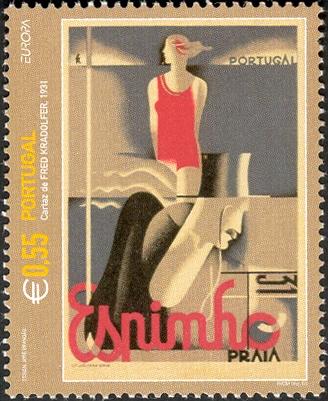
Fred Kradolfer (Zurique, 1903 - Lisboa, 1968)Chegado a Portugal em 1928, este suíço foi o mentor das artes da decoração e da publicidade para a segunda geração de artistas modernistas.Artista multifacetado, impulsionou o desenvolvimento das artes gráficas em Portugal, tendo usado a sua criatividade em diversos meios, do cartaz ao vitral, da cerâmica aos anúncios luminosos. Fred K. foi o gráfico que revolucionou o cartaz em Portugal na década de 50. Completou o curso de Ourivesaria na Escola de Artes e Ofícios, em Zurique. Chegou a Portugal no final da década de 20, após ter vivido na Bélgica e em Paris, pertencendo ao grupo artístico promovido por António Ferro. Trabalhou como decorador na Exposição Colonial (1931) e na Exposição Internacional (1937), ambas em Paris, na Exposição Internacional de Nova Iorque (1939) e na Exposição do Mundo Português (1940). O seu trabalho foi desenvolvido juntamente com artistas consagrados (Bernardo Marques, Carlos Botelho, Emmerico Nunes, José Rocha, Paulo Ferreira e Thomaz de Mello), grupo conhecido como a "equipa de António Ferro" ou a "equipa do SPN (Secretariado de Propaganda Nacional).
FK representou elementos do folclore, estilizados, em objectos de uso quotidiano (bilha, pote, espiga, flores, etc.) e da vida campestre (porcos, touros, cavalos, burros, etc.), típicos na altura, introduzindo uma certa modernidade no posicionamento das figuras. Em lambrilhas, pelo seu carácter funcional e decorativo, experimentou a combinação de motivos e elementos ornamentais. Exposição Internacional de Paris, 1937A decoração do Pavilhão Português apresentado na Exposição Internacional de Paris, de 1937, foi uma das mais notáveis realizações plásticas da década, internacionalmente reconhecida, e esteve a cargo de uma equipa constituída por Fred Kradolfer, que a liderou, e pelos pintores Bernardo Marques, José Rocha, Carlos Botelho, Tom, Emmerico Nunes e Paulo Ferreira. Em 1944 participou, juntamente com Bernardo Marques, Carlos Botelho, José Rocha e José Luís Brandão, na decoração dos stands da Feira Popular pertencentes à Junta Nacional do Vinho, ao Instituto Português de Conservas de Peixe e à Junta Nacional da Cortiça.
Relacionado com estes serviços, Kradolfer executou um grande número de rótulos e cartazes publicitários. Esteve bastante ligado à fundação do Estúdio Técnico de Publicidade, onde demonstrou toda a sua criatividade, chegando a decorar montras, bastante solicitadas e admiradas. Não possuindo os conhecimentos necessários para o domínio das técnicas e processos de fabrico em azulejaria e cerâmica, efectuava projectos que depois eram executados na Fábrica Viúva Lamego. Aliás, foi muito curta a sua passagem pela cerâmica, nomeadamente com as lambrilhas utilizadas nas exposições em que participou com o "grupo do SPN", actividade só retomada em 1955-57 através da encomenda de dois painéis para o Hotel Infante Santo. Em 1957, encomendaram-lhe diversas placas cerâmicas com os nomes dos pesqueiros da zona da Boca do Inferno, em Cascais, destruídos mais tarde. Nesse ano, recebeu também uma encomenda para o revestimento parietal da sede da Soponata, na Rua do Açúcar, em Lisboa (efectuou, igualmente, toda a decoração interior deste edifício, dotando-a de grande dinamismo). Utilizando uma estética diferente, realizou o revestimento parietal da capela do Aquartelamento de Santa Margarida, tendo concebido os azulejos do baptistério, do arco do triunfo e das paredes laterais da capela. Executou, igualmente, os vitrais e a tábua do altar que representa Santa Margarida. No Casino Estoril decorou o fundo do espelho de água interior do Jardim de Inverno (1966), com azulejos de várias cores (mais tarde destruído). Para o Hotel Estoril-Sol executou cinco painéis cerâmicos. Em 1965, realizou azulejos para o Cinema Europa e para a fachada do edifício da Reitoria da Universidade de Lisboa. O Museu Nacional do Azulejo possui algumas das suas peças cerâmicas. FK também terá trabalhado na Fábrica Lusitânia nos anos 30, efectuando anúncios em azulejo.